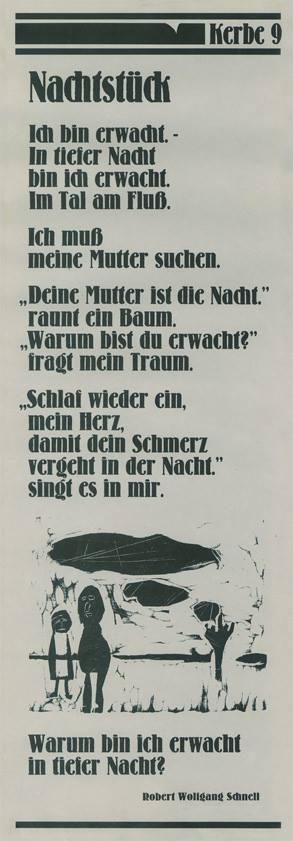
Nicht die Bernhard Antique
Jedenfalls nicht ganz. Ein Freund frug mich nach der Schrift, und kurz nach dem Aufstehen dachte ich verschwiemelt: »Bernhard Antique«. aber die ist es nicht. Es liegt mir auf der Zunge, ich komme aber nicht drauf.
Eigentlich nichts, aber es wurmt mich halt, dass es nicht ganz die BA ist und ich nicht weiß, welche. :-)
Wo kommt das denn her? Es sieht schon älter aus. Ist es vielleicht Plakatschrift in Holz oder Blei oder so, und dass die etwas anders gezeichnet ist als die neueren digitalen Versionen :-?
Wann und wie wurde das denn gedruckt?
Wenn ein kein digitaler Satz ist, würde das eventuelle Unterschiede erklären. Wenn es digital ist, sollte man die anderen Bernhard-Antiqua-Digitalisierungen durchgehen. Gibt ja noch mehr. Dass es eine gänzlich andere Schrift ist, glaube ich eher nicht.
Glaube ich auch nicht.
Ich habe jetzt mal einige digitale Versionen durchgeschaut, finde diese Bernhard-Antique-Variante nicht. Die Vorlage ist mit Sicherheit nicht digital, daran wird es liegen.